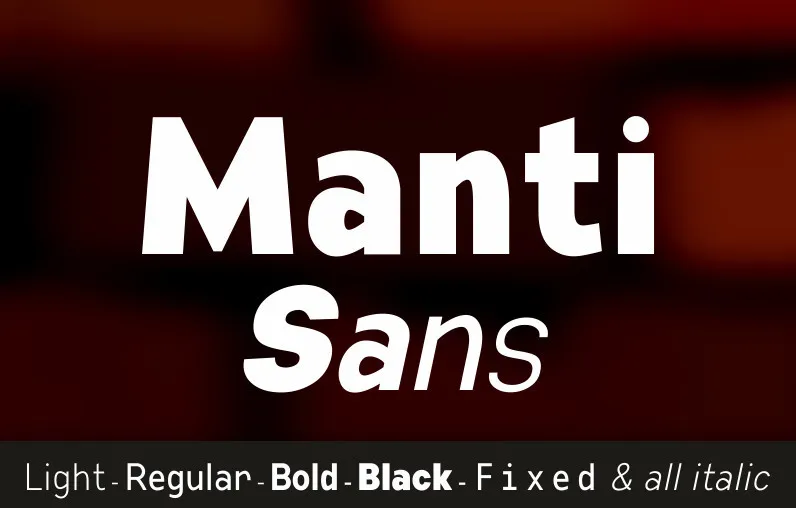
Aqui está uma descrição curta e envolvente para a página de download da font ‘Manti Sans Font Family’, seguindo as orientações fornecidas: Introduzimos Manti Sans, uma família universal de tipografia sans serif, perfeita tanto para identidades de marca quanto para design editorial. Suave e contemporânea ao mesmo tempo, esta fonte moderna é ideal para cobrir um vasto leque de necessidades. Confortável para grandes títulos e headlines, ela se destaca em elementos como páginas web, cartazes, logotipos, anúncios e campanhas promocionais. Com seu peso mais pesado, Manti Sans é perfeito para criar impacto visual. Esta família de fontes inclui caracteres multilíngues, garantindo que você possa explorar diferentes idiomas sem qualquer problema adicional. Ideal tanto para projetos profissionais quanto para iniciantes na tipografia, a Manti Sans é uma escolha inteligente para designers gráficos e empreendedores digitais. Descubra por si mesmo o poder desta fonte versátil e moderna, ideal tanto para estilos tradicionais quanto contemporâneos de design.